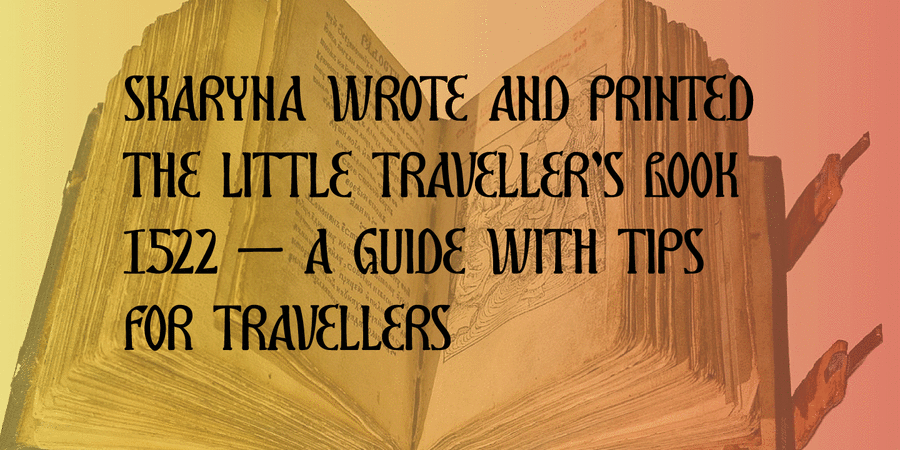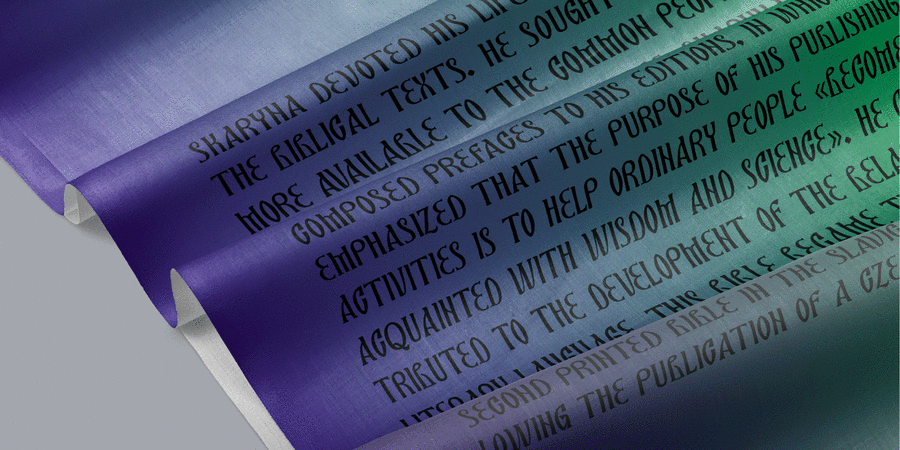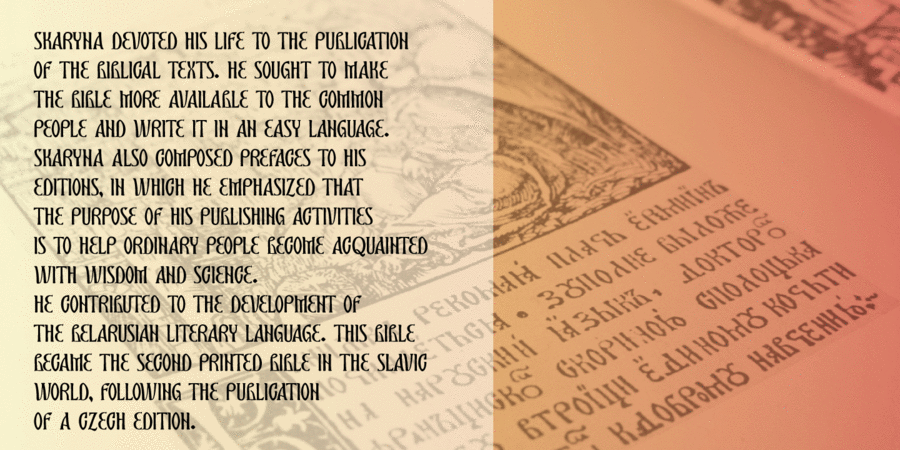
Skaryna 2017 Title – це реконструкція оригінального шрифту, розробленого Франциском Скориною в 1517–1519 роках. Цифровий шрифт створений на честь 500-річчя оригінальної роботи Франциска Скорини (лат. Franciscus Scorina de Poloczko) – вченого і просвітника з Полоцька (нинішня Білорусь). Оригінальний дизайн містив лише кириличні символи, а в реконструкцію були додані латинські символи та додаткові знаки, щоб зробити спадщину Франциска доступним для усього світу. Шрифт Скорини відтворений близько до оригіналу, тому він залишається трохи неточним, як і технології друку раннього Відродження. Спонсором проекту виступив Антон Бриль. Шрифт розробив Олексій Коваль у 2020 році.